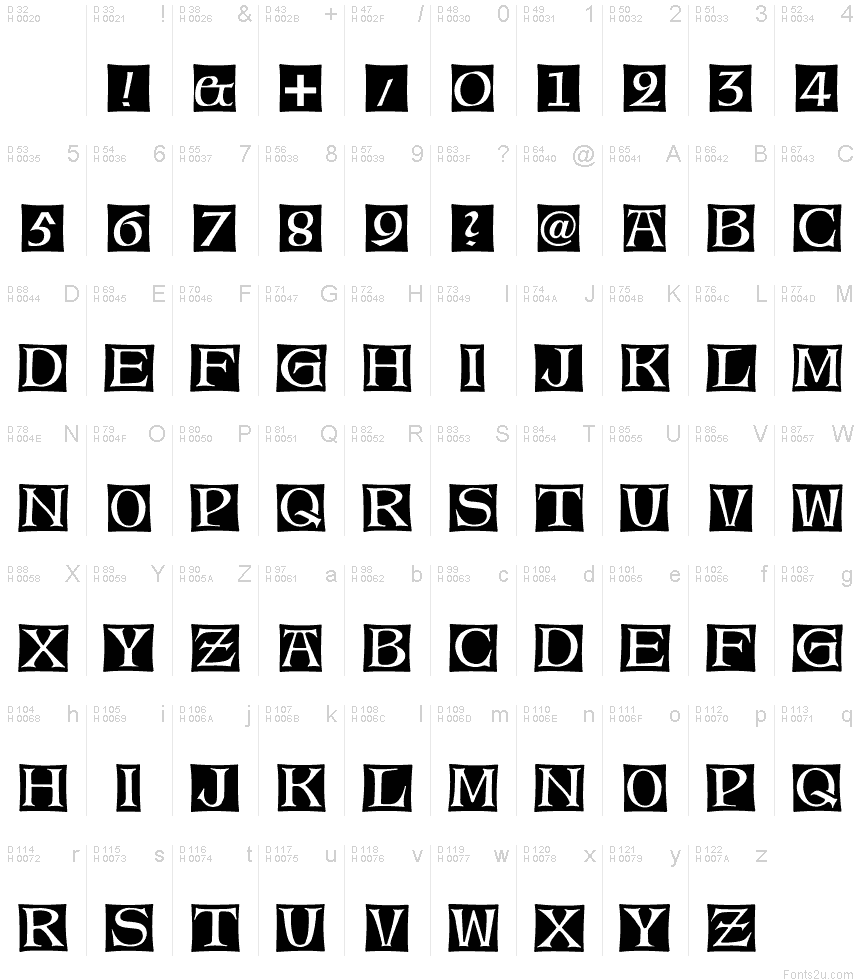
Alte Caps od Typographer Mediengestaltung to darmowy gotycki krój pisma, który przypomina litery wykute w kamiennych blokach. Każdy znak znajduje się w gęstym czarnym prostokącie, z ostrymi, ciosanymi białymi formami, które wyglądają surowo i nieco nierówno, co nadaje krojowi drapieżny, średniowieczny charakter. Całość przypomina rząd wygrawerowanych płytek – jest odważna i złowieszcza, błyskawicznie nadając projektom mroczny, starodawny klimat.
Dzięki Alte Caps tytuły i logotypy stają się głośne, ciężkie i niezapomniane. To sprawia, że ten darmowy font jest naturalnym wyborem dla logotypów zespołów metalowych, plakatów koncertowych, okładek książek dark fantasy, tytułów filmów grozy, ekranów startowych gier czy grafik na gadżety. Świetnie sprawdza się w dużych rozmiarach, gdzie masywne czarne kwadraty i poszarpane kontury naprawdę robią wrażenie. W tekście głównym połącz go z czystym, neutralnym krojem bezszeryfowym, aby zachować czytelność układu, podczas gdy Alte Caps zajmie się całą resztą dramatyzmu.